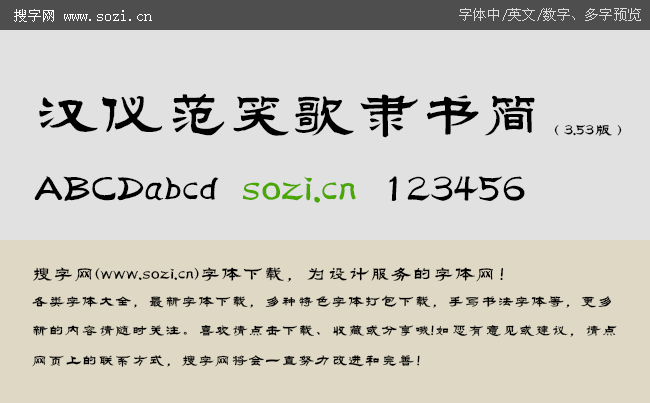
漢儀范笑歌隸書簡
搜字網(wǎng)給大家提供一款有古典風(fēng)味的漢儀范笑歌隸書簡體下載。范笑歌隸書具有魏碑的筆畫筆意,并有篆書的韻味風(fēng)格,其中的范橫畫是范體隸書特有獨創(chuàng)的筆畫,如同舒展的雙翅,使隸書中的蠶頭燕尾更張揚,更有力度。范橫畫改變了千百年來隸書的蠶頭燕尾的程式寫法,整個字體風(fēng)格剛?cè)嵯酀瑸t灑舒展,具有很強的裝飾性。此款字體適用于書籍、畫報的主副標(biāo)題和個性品牌設(shè)計推廣等環(huán)境。